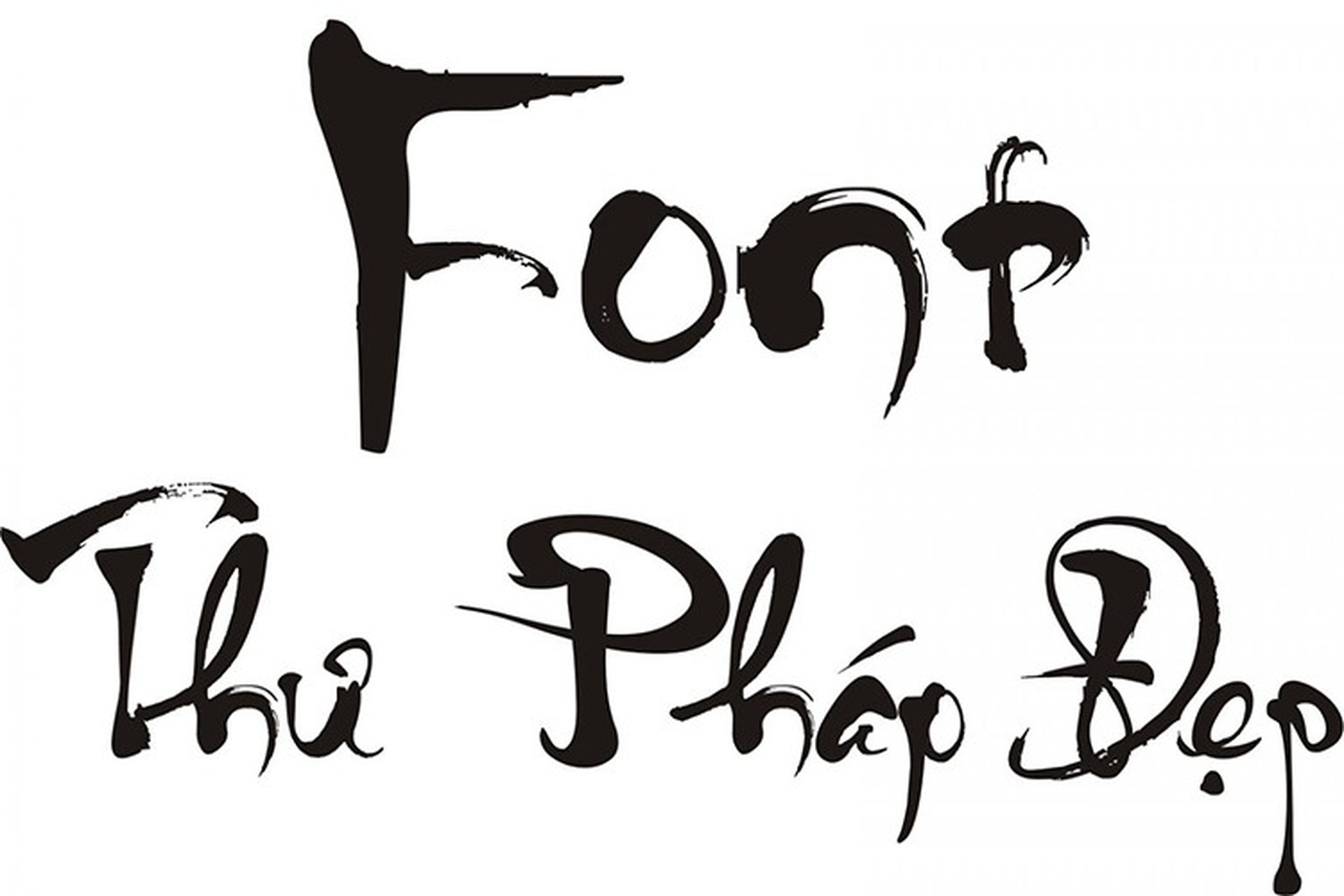
Giới thiệu về font thư pháp
Trong xã hội hiện đại, font thư pháp không chỉ đơn thuần là những ký tự được thiết kế trên máy tính mà còn là sự kết hợp hài hòa giữa nghệ thuật và công nghệ. Sự phát triển của công nghệ thông tin đã mở ra nhiều cơ hội cho việc tạo ra và sử dụng font thư pháp, từ đó góp phần làm phong phú thêm đời sống nghệ thuật.
Khái niệm font thư pháp
Font thư pháp có thể được hiểu là kiểu chữ được thiết kế với sự chú ý đặc biệt đến đường nét và hình dáng chữ. Nó thường thể hiện sự mềm mại, uyển chuyển và mang tính nghệ thuật cao. Nét vẽ của từng chữ cái không chỉ đơn thuần là để truyền đạt thông tin mà còn để gây ấn tượng và cảm xúc cho người nhìn.
Khi nói đến font thư pháp, chúng ta thường liên tưởng đến những giá trị văn hóa và truyền thống. Mỗi loại font thư pháp đều mang trong mình một câu chuyện riêng, phản ánh tâm tư, tình cảm và triết lý sống của người viết.
Lịch sử phát triển của thư pháp
Thư pháp đã xuất hiện từ rất lâu trong lịch sử nhân loại, bắt nguồn từ nhu cầu giao tiếp và ghi chép. Tại Việt Nam, thư pháp đã phát triển qua nhiều giai đoạn lịch sử, từ thời kỳ Hán thuộc đến thời kỳ độc lập. Mỗi thời kỳ đều có những ảnh hưởng nhất định tới kiểu chữ thư pháp, từ đó tạo nên sự đa dạng và phong phú trong phong cách viết.
Thư pháp Trung Quốc cũng có một lịch sử lâu đời không kém, với nhiều trường phái khác nhau. Từ những nét bút đầu tiên, thư pháp đã trở thành một bộ môn nghệ thuật độc đáo, phản ánh tinh thần dân tộc và bản sắc văn hóa của đất nước.
Tầm quan trọng của thư pháp trong văn hóa Việt Nam và Trung Quốc
Thư pháp không chỉ là một nghệ thuật viết chữ mà còn là một phần của di sản văn hóa. Ở Việt Nam, thư pháp được coi là biểu tượng của trí thức và sự thanh tao. Những bức tranh thư pháp thường được treo trong nhà để cầu mong tài lộc, bình an.
Tương tự, ở Trung Quốc, thư pháp được xem là một trong “tứ bá” (thơ, thư, họa, nhạc), thể hiện sự hòa quyện giữa cái đẹp và tri thức. Người Trung Quốc luôn tôn sùng nghệ thuật thư pháp như một cách thể hiện lòng tự hào dân tộc và văn hóa truyền thống.
Các loại font thư pháp
Việc phân loại font thư pháp là điều cần thiết để người dùng có thể lựa chọn dễ dàng hơn. Có hai loại chính là font thư pháp truyền thống và font thư pháp hiện đại. Mỗi loại đều có những đặc trưng riêng, phục vụ cho những mục đích khác nhau trong cuộc sống.
Font thư pháp truyền thống
Font thư pháp truyền thống thường mang đậm dấu ấn văn hóa cổ điển. Những nét chữ được vẽ bằng bút lông, thể hiện sự tinh tế và chất liệu truyền thống. Đây là loại font được yêu thích bởi những người có sở thích sưu tầm hoặc tìm kiếm sự hoài cổ.
Người sử dụng font thư pháp truyền thống thường tìm kiếm sự kết nối với quá khứ, nơi mà mỗi chữ viết đều mang trong mình một giá trị văn hóa. Chính vì vậy, các tác phẩm nghệ thuật được tạo ra từ font thư pháp truyền thống thường có sức sống lâu dài và giá trị thẩm mỹ cao.
Font thư pháp hiện đại
Khác với font thư pháp truyền thống, font thư pháp hiện đại có tính linh hoạt và đổi mới hơn. Các nhà thiết kế đã áp dụng nhiều công nghệ mới để tạo ra những kiểu chữ độc đáo, phù hợp với xu hướng hiện nay.
Font thư pháp hiện đại thường được sử dụng trong quảng cáo, thiết kế đồ họa và truyền thông. Một số thiết kế còn kết hợp cả yếu tố hiện đại và truyền thống, tạo nên sự phong phú cho thị trường font chữ.
So sánh giữa font thư pháp Việt Nam và Trung Quốc
Mặc dù có nhiều điểm tương đồng, font thư pháp Việt Nam và Trung Quốc vẫn tồn tại những sự khác biệt rõ rệt. Font thư pháp Trung Quốc thường có độ phức tạp cao hơn với nhiều nét vẽ uốn cong, trong khi font thư pháp Việt Nam lại thiên về sự đơn giản và dễ đọc.
Sự khác biệt này không chỉ nằm ở hình thức mà còn ở nội dung. Font thư pháp Việt Nam thường mang nội dung gần gũi với cuộc sống hàng ngày, trong khi thư pháp Trung Quốc lại chứa đựng nhiều triết lý sâu sắc hơn.
Cách chọn font thư pháp đẹp
Với sự đa dạng của các loại font thư pháp, việc lựa chọn một font chữ đẹp là điều không hề đơn giản. Dưới đây là một số tiêu chí và lưu ý giúp bạn có thể chọn được font thư pháp phù hợp.
Tiêu chí đánh giá font thư pháp
Khi chọn font thư pháp, người dùng nên căn cứ vào các yếu tố như độ chân thực, tính thẩm mỹ và khả năng truyền tải thông điệp. Một font thư pháp đẹp cần phải có sự cân đối giữa các nét vẽ, đảm bảo rằng nó không chỉ đẹp mà còn dễ đọc.
Ngoài ra, độ sắc nét của mỗi chữ cũng đóng vai trò quan trọng. Một font chữ sắc nét sẽ khiến tác phẩm trở nên nổi bật hơn và gây ấn tượng với người nhìn.
Các phong cách thư pháp phổ biến
Có rất nhiều phong cách thư pháp khác nhau, từ cổ điển đến hiện đại. Một số phong cách nổi bật bao gồm:
- Thư pháp Uốn Lượn: Nét chữ mềm mại và uyển chuyển, thường được sử dụng trong các tác phẩm nghệ thuật.
- Thư pháp Gạch Ngang: Nét chữ mạnh mẽ và chắc chắn, thường phù hợp với các thiết kế hiện đại. Việc lựa chọn phong cách thư pháp phù hợp sẽ giúp bạn truyền tải tốt hơn thông điệp mà mình muốn gửi gắm.
Những lưu ý khi sử dụng font thư pháp
Khi sử dụng font thư pháp, bạn cũng cần lưu ý đến ngữ cảnh và đối tượng người nhận. Font thư pháp có thể không phù hợp trong tất cả các tình huống. Nếu bạn đang thiết kế một sản phẩm thương mại, hãy cân nhắc kỹ lưỡng trước khi quyết định sử dụng font chữ này.
Một điểm quan trọng nữa là cần kiểm tra tính tương thích của font thư pháp với các phần mềm mà bạn đang sử dụng. Một số font có thể không hiển thị đúng trên tất cả các nền tảng, ảnh hưởng đến trải nghiệm người dùng.
Hướng dẫn tải font thư pháp
Việc tải và cài đặt Font Thư Pháp rất đơn giản, chỉ cần vài bước là bạn đã có thể sử dụng font thư pháp đẹp mắt cho công việc sáng tạo của mình. Cùng theo dõi các bước dưới đây để thực hiện nhé!
Bước 1: Tải Font Thư Pháp Việt Hóa về máy
- Link tải Font Thư Pháp Việt Hóa [tại đây].
Bước 2: Giải nén file vừa tải
- Click chuột phải vào file tải về => Chọn “Extract Here” để giải nén bằng phần mềm WinRAR.
Bước 3: Mở thư mục Font Thư Pháp đã giải nén
- Vào thư mục Font trong thư mục font-thu-phap vừa giải nén.
Bước 4: Sao chép Font Thư Pháp
- Nhấn tổ hợp phím Ctrl + A để chọn toàn bộ font thư pháp => Nhấn tổ hợp Ctrl + C để sao chép.
Bước 5: Truy cập thư mục Fonts trên máy tính
- Mở thư mục C:/Windows/Fonts.
Bước 6: Dán Font vào thư mục Fonts
- Nhấn Ctrl + V để dán font thư pháp vào thư mục Fonts của máy tính.
Bước 7: Sử dụng Font Thư Pháp
- Mở phần mềm soạn thảo hoặc chỉnh sửa ảnh như Photoshop, Word, và chọn Font Thư Pháp để bắt đầu sáng tạo những tác phẩm thư pháp độc đáo!
Ứng dụng của font thư pháp trong đời sống
Font thư pháp không chỉ dừng lại ở lĩnh vực nghệ thuật mà còn có mặt trong nhiều khía cạnh của đời sống hàng ngày. Dưới đây là một số ứng dụng phổ biến.
Sử dụng font thư pháp trong trang trí
Nhiều người chọn font thư pháp để trang trí nhà cửa, từ việc in tranh thư pháp treo tường cho đến việc thiết kế các thiệp mời.
Các bức tranh thư pháp không chỉ mang lại giá trị thẩm mỹ mà còn thể hiện phong cách và cá tính của gia chủ. Một không gian sống được trang trí bằng thư pháp sẽ trở nên ấm cúng và thu hút hơn.
Vai trò của thư pháp trong các sự kiện văn hóa
Trong các sự kiện văn hóa, font thư pháp thường được sử dụng để thể hiện bản sắc dân tộc và tôn vinh truyền thống. Các lễ hội, triễn lãm thư pháp hay các buổi giao lưu văn hóa thường không thể thiếu sự hiện diện của thư pháp.
Những bức thư pháp tại các sự kiện này thường mang lại cảm giác trang trọng và sang trọng, thể hiện sự kính trọng đối với văn hóa và nghệ thuật.
Font thư pháp trong nghệ thuật và sáng tạo
Font thư pháp không chỉ đơn thuần là một phương tiện truyền tải thông điệp mà còn truyền cảm hứng cho nhiều nghệ sĩ. Những nghệ sĩ sử dụng font thư pháp trong tác phẩm của mình thường mang đến một cái nhìn mới mẻ và sáng tạo, từ đó tạo ra những tác phẩm ấn tượng và độc đáo.
Việc kết hợp thư pháp với các hình thức nghệ thuật khác như hội họa, điêu khắc hay nhiếp ảnh cũng là một trong những xu hướng trong giới nghệ sĩ hiện nay.
Trong thế giới hiện đại, font thư pháp không chỉ đơn thuần là một kiểu chữ mà còn là một phần quan trọng trong văn hóa và nghệ thuật. Với sự phát triển của công nghệ, việc sử dụng thư pháp ngày càng trở nên phổ biến và dễ dàng hơn.
Hy vọng rằng qua bài viết này, bạn đã có cái nhìn tổng quát hơn về font thư pháp và những ứng dụng của nó trong đời sống. Hãy khám phá và trải nghiệm nghệ thuật thư pháp để cảm nhận vẻ đẹp tiềm ẩn của nó!